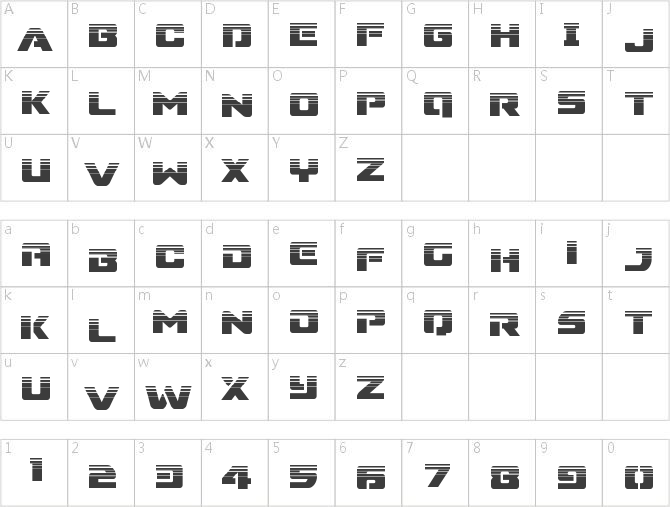
Super Commando Halftone 詳情頁
Super Commando Halftone字體字庫是一款讓人賞心悅目、百看不厭的英文字體,適合各類廣告和產(chǎn)品包裝設(shè)計(jì)應(yīng)用,字體大小0.04MB,格式為ttf字體,上傳用戶是小籃子,作者/版權(quán)方為未知